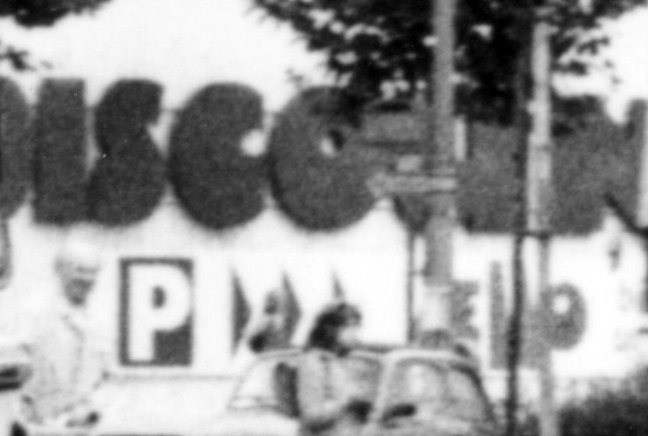
Supermarkt-Schrift aus den 70er Jahren gesucht
Ob denn wohl jemand diese alte Schrift zu identifizieren vermag?
Es handelt sich um einen Fotoausschnitt aus dem Jahr 1977 ... Bessere Qualiät leider nicht vorhanden.
Dazu gehört der obere Teil, wo da steht "DISCOUNT", und darunter "SELLO" (letzteres eher klein und leider hinter einem Baum etwas versteckt. Das "L" von "Sello" ist auf der linken Seite gerade und auf der rechten fällt es schräg ab (wird nach unten hin dicker). Ich hoffe, daß man den Rest einigermaßen erkennt.
Das Wort "Sello" scheint aber nicht exakt mit dem Schriftzug "Discount" identisch zu sein. Wenn ich mir das "o" angucke, sieht das in Discount anders aus als in Sello (das Loch darin ist irgendwie nicht nur proportional anders, sondern scheint auch anders plaziert zu sein).